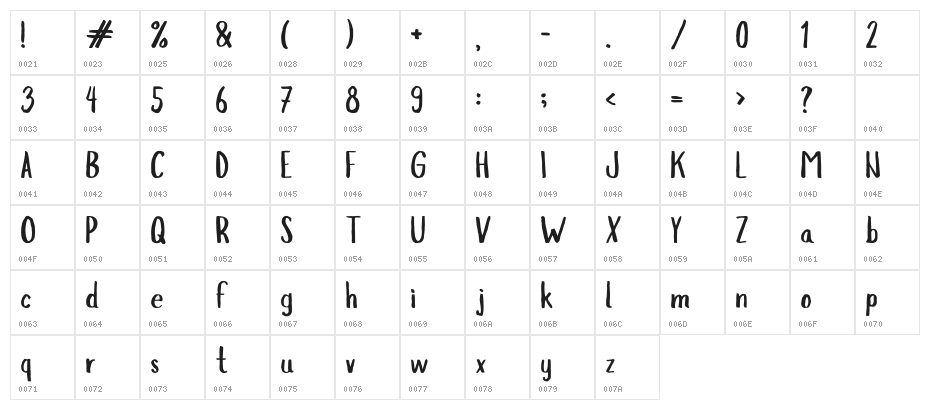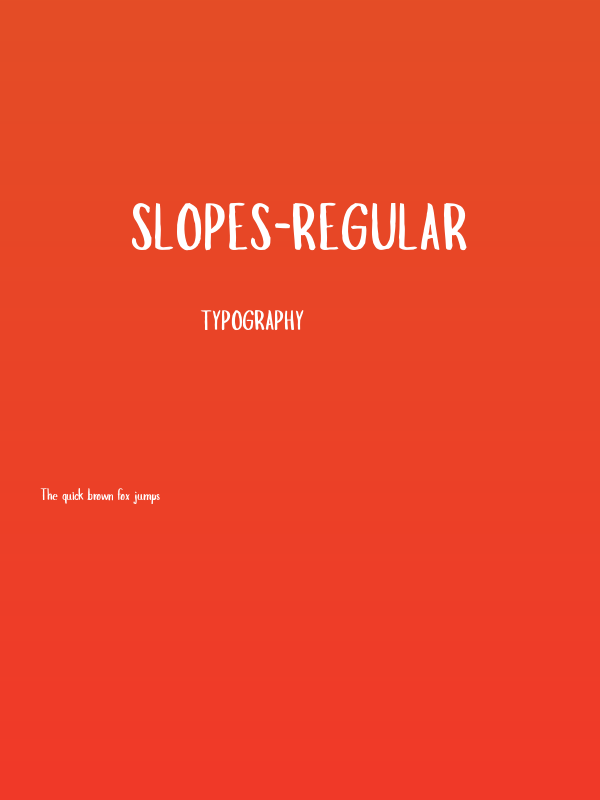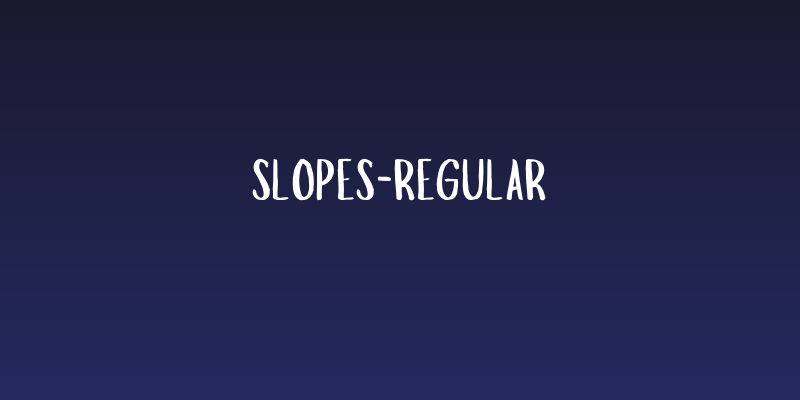
Slopes-Regular Font
| Stile generale | Casual, Playful |
| Caso d'uso | Headlines, Logos, Informal Text |
| Progetti proposti | Ideal for greeting cards, invitations, posters, and branding projects that require a personal and informal touch. |